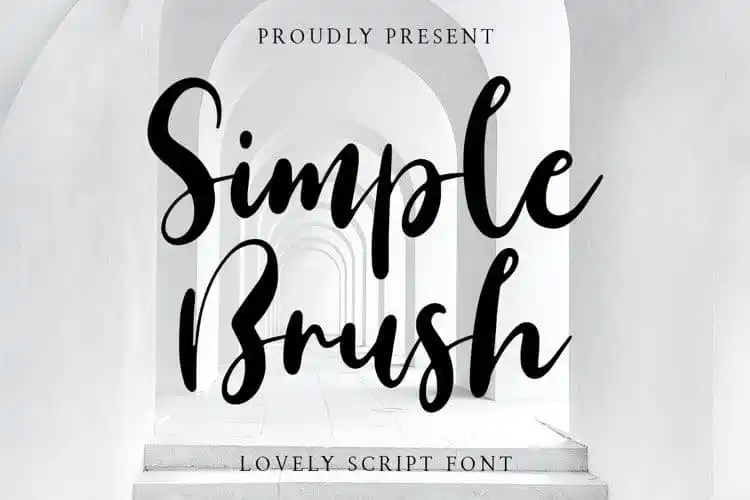
Simple Script Font – Download Grátis
A fonte Simple Script é perfeita para qualquer designer criativo. Ela traz uma sensação natural e autêntica a cada detalhe de seu design. Essa tipografia foi criada pela Typesthetic Studio, com um estilo moderno e brush calligraphy, onde todas as linhas foram criadas à mão, oferecendo um toque sofisticado de fluidez. Perfeita para logotipos, decoração de casamentos, cartões personalizados, designs de presentes, fotografia e até mesmo como marca d’água em embalagens de produtos ou citações escritas à mão. O uso de ligaturas, conjunto completo de letras maiúsculas e minúsculas, símbolos multilíngues, números e pontuação fazem do Simple Script uma fonte versátil que se encaixa em um amplo leque de aplicativos gráficos. Descubra o toque autêntico e sofisticado que este tipo face traz a seus projetos. Seja para dar vida à sua identidade visual, personalizar suas mensagens ou apenas adicionar um toque único e criativo ao seu design.